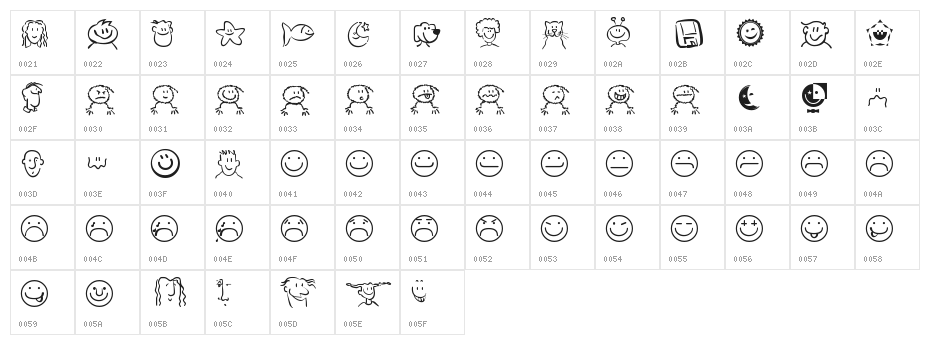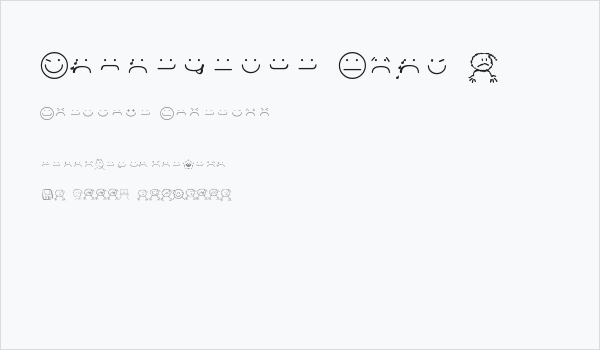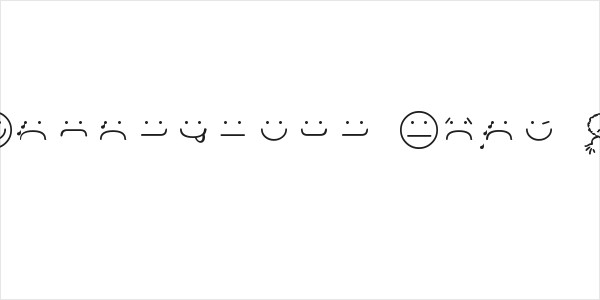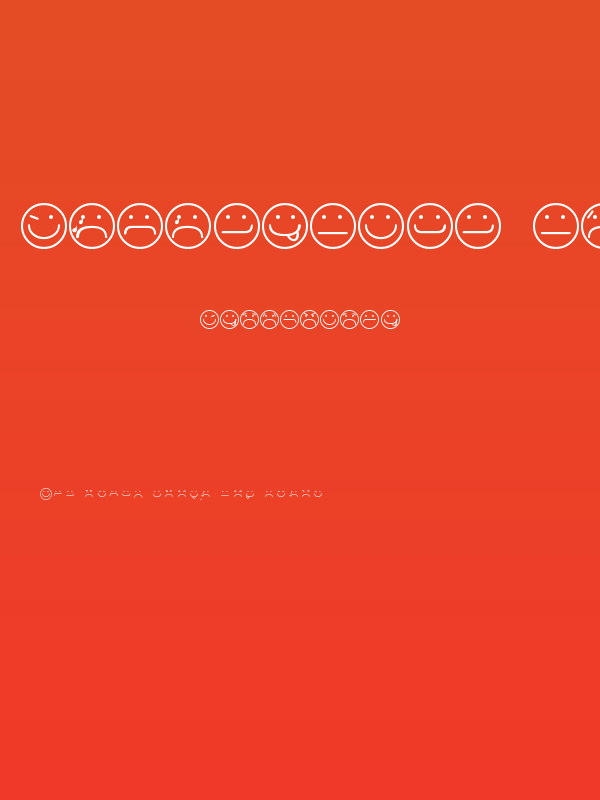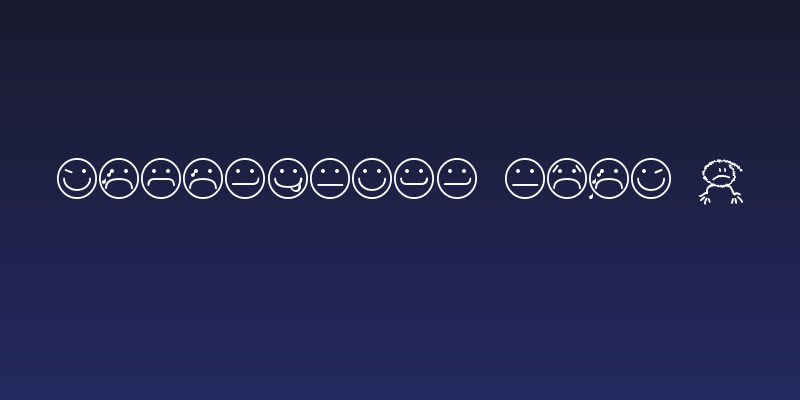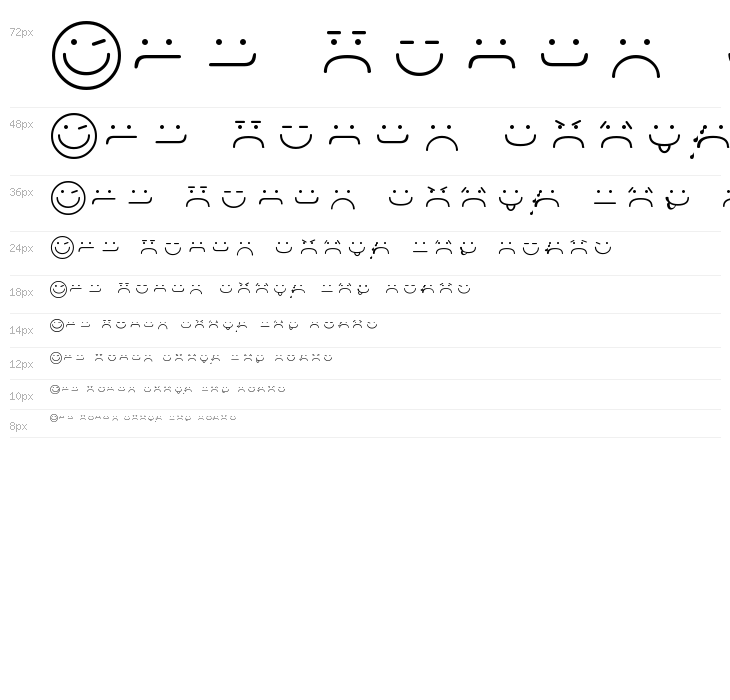
Smileyface Font 3 Font
| Caz de utilizare | Logos, Creative projects, Children's materials |
| Proiecte propuse | Ideal for children's books, playful branding, greeting cards, and creative projects that require a fun and expressive touch. |